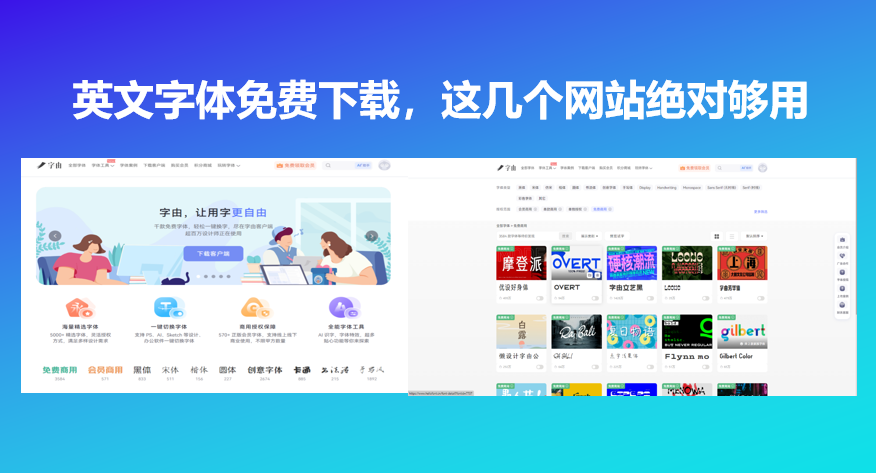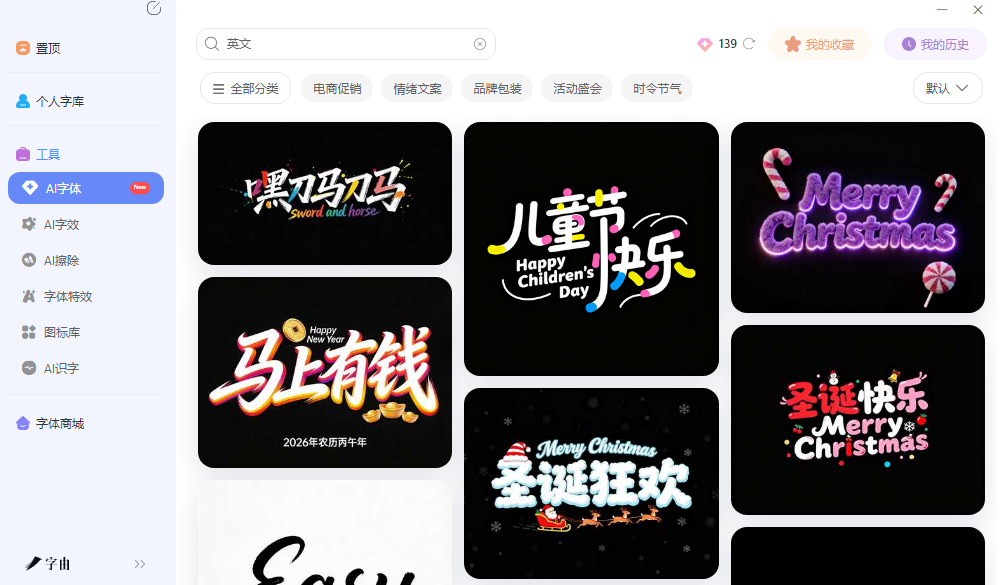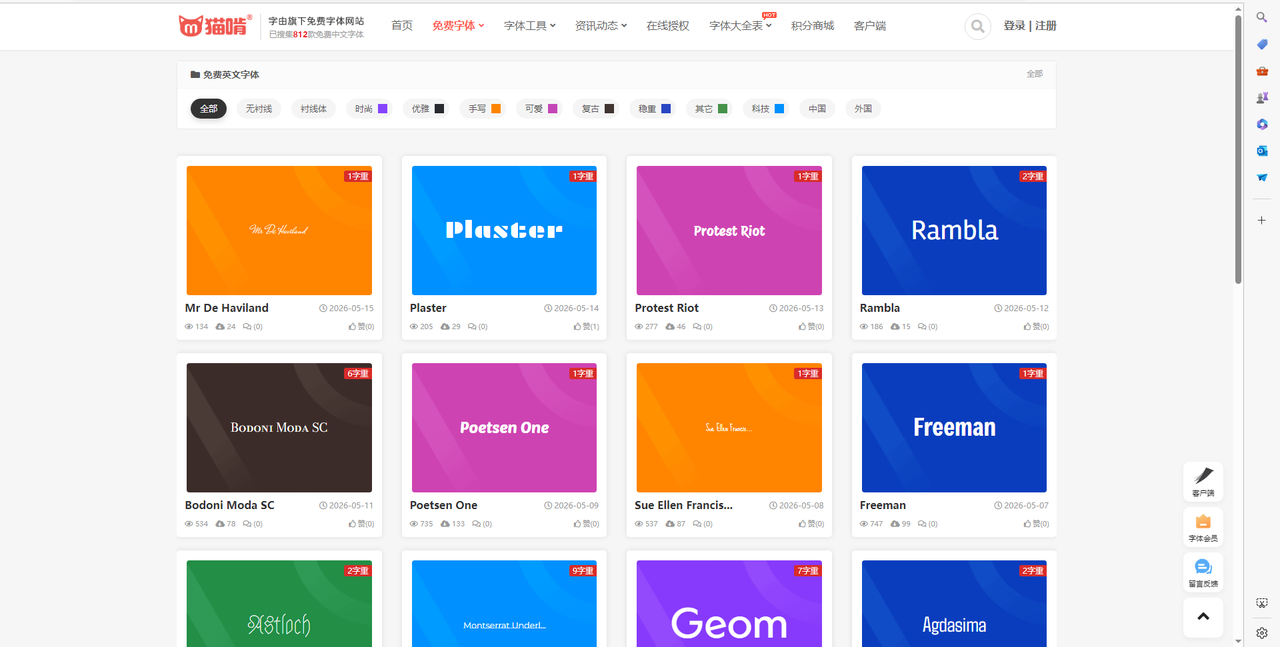
英文字体免费下载,这几个网站绝对够用
打开PS准备做一张英文海报,字体下拉菜单翻来翻去就那么几款:Arial、Times New Roman、Helvetica。不是不好用,是每个项目都用,做出来的东西跟别人的放在一起,分不清是谁的。去网上搜“免费英文字体”,结果不是收费就是版权不明,要么下载流程繁琐得让人想放弃。其实真正好用的免费英文字体下载站就那几个,有的不用下载直接激活,有的精选开源字库,有的分类细致到能按风格一键筛选。今天说5个我亲测好用的渠道,从字由的云端激活到垂直开源站,每个都能让你找到既免费又能放心用的英文字体。
字由和传统字体下载站最大的区别是:你不需要下载任何字体文件。打开字由客户端,里面收录了上万款字体,其中免费商用英文字体占了相当比重。字由的英文字体按风格分得很细。无衬线体适合现代简洁的设计,衬线体适合经典优雅的排版,手写体适合邀请函和个性标题,等宽体适合代码和科技感设计。每款字体都可以实时预览——输入你自己的文案“Hello World”,页面立刻显示效果,不用激活就能判断合不合适。
找到喜欢的英文字体后,点击“激活”按钮。字体立刻出现在你的PS、AI、Word字体列表里,不用下载安装包,不用解压,不用重启软件。换电脑时登录同一个字由账号,之前激活的字体一键同步,不用重新下载。对于经常在多台设备之间切换的设计师来说,字由是最省事的方案。
字由的AI字体功能也可以生成英文艺术字。在AI模板里搜索“英文字体”“霓虹”“金属”,选一个模板输入英文,生成高清PNG图片,背景透明,直接放在海报里。如果你只需要一张特效英文标题图,AI字体是更快的路子。
2、猫啃网
第二个网站是猫啃网。它自称“字由旗下免费字体网站”,已搜集812款免费中文字体,同时也收录了大量高品质免费英文字体。从第一张截图可以看到,它专门设有“免费英文字体”板块,分类包括无衬线、时尚、优雅、可爱、复古、稳重、科技、中国、外国等。用户可以根据项目调性快速筛选。主页展示了多款免费英文字体:Mr De Haviland(手写花体)、Plaster(粗犷展示体)、Protest Riot(街头风格)、Rambla(优雅无衬线)、Bodoni Moda SC(经典衬线)、Poetsen One(圆润标题体)、Sue Ellen Francisco(手写草书)、Freeman(现代粗体)、Agdasima等。
猫啃网的字体会员专区还提供了多字重字体,如6字重、9字重、7字重的完整家族,适合需要精细排版的专业项目。下载方式:点击字体进入详情页,找到下载链接即可获取TTF或OTF文件。这个站的特点是更新快、分类细,而且所有字体都经过授权确认,免费商用有保障。如果你习惯下载字体文件安装到电脑里使用,猫啃网是首选。
3、Feroniapi
第三个网站是一个单体字体下载页面。它展示了“Mating curry wurst”字样和“Feroniapi”字体,由Peter Wiegel设计,并有Julienne Richard的贡献。页面提供了“Download”按钮。这类单体字体站通常由设计师个人维护,字体质量高,且大多免费商用。Feroniapi是一款带有手写感或装饰感的英文字体,适合标题或短句。单体字体站的优势是直接、无广告、下载快速。缺点是字体数量少,需要用户主动搜索。如果你已经知道想要的具体字体名称,或者喜欢挖掘小众设计师的作品,可以关注这类站点。通常从设计师的个人网站或Behance页面找到下载链接。下载后直接安装到系统字体文件夹即可使用,注意查看字体包内的授权说明。
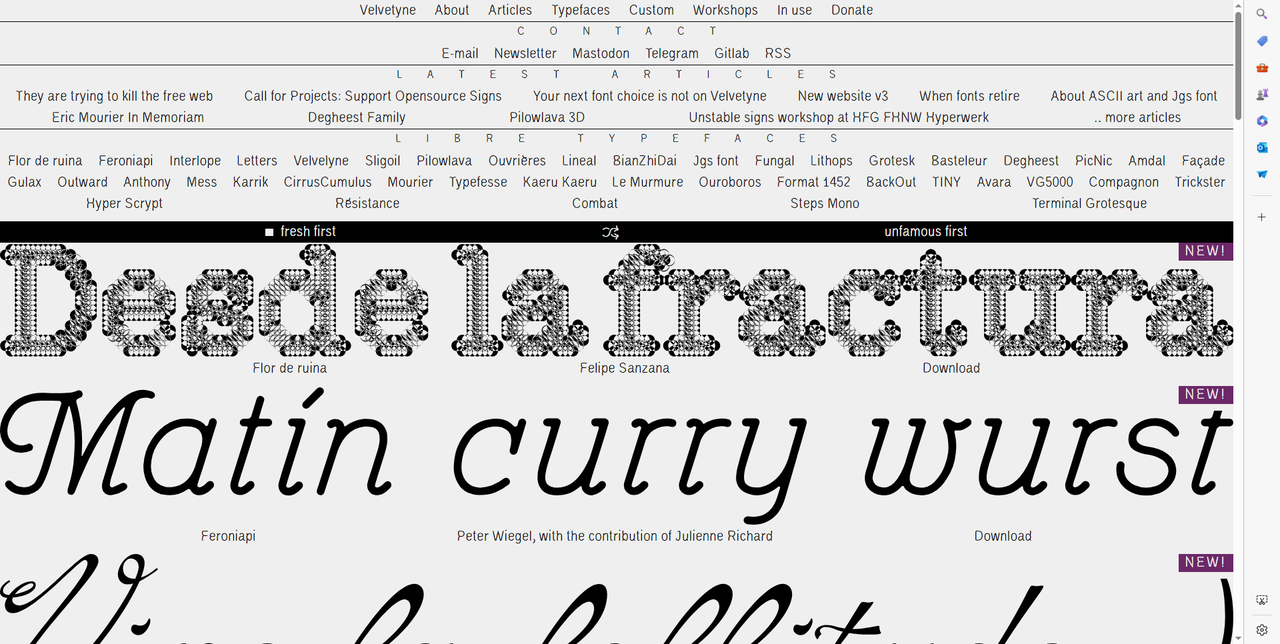
4、Open Foundry
第四个网站是Open Foundry。这是一个专注于开源字体的平台,界面极简。截图显示它展示了“M+ M Type-1”等开源字体,并提供“Subscribe”订阅功能。Open Foundry的字体大多是SIL OFL协议或CC0协议,可免费用于个人和商业项目,并且允许修改和再分发。Open Foundry的风格偏向现代、极简、实验性,收录的字体不像传统字体站那么多,但每款都是精品。如果你需要一款有设计感、不落俗套的开源英文字体,这里值得一逛。下载方式:点击字体卡片进入详情页,找到下载链接或GitHub仓库。这个站适合追求独特、不撞字体的设计师,以及需要嵌入网页的开源项目。
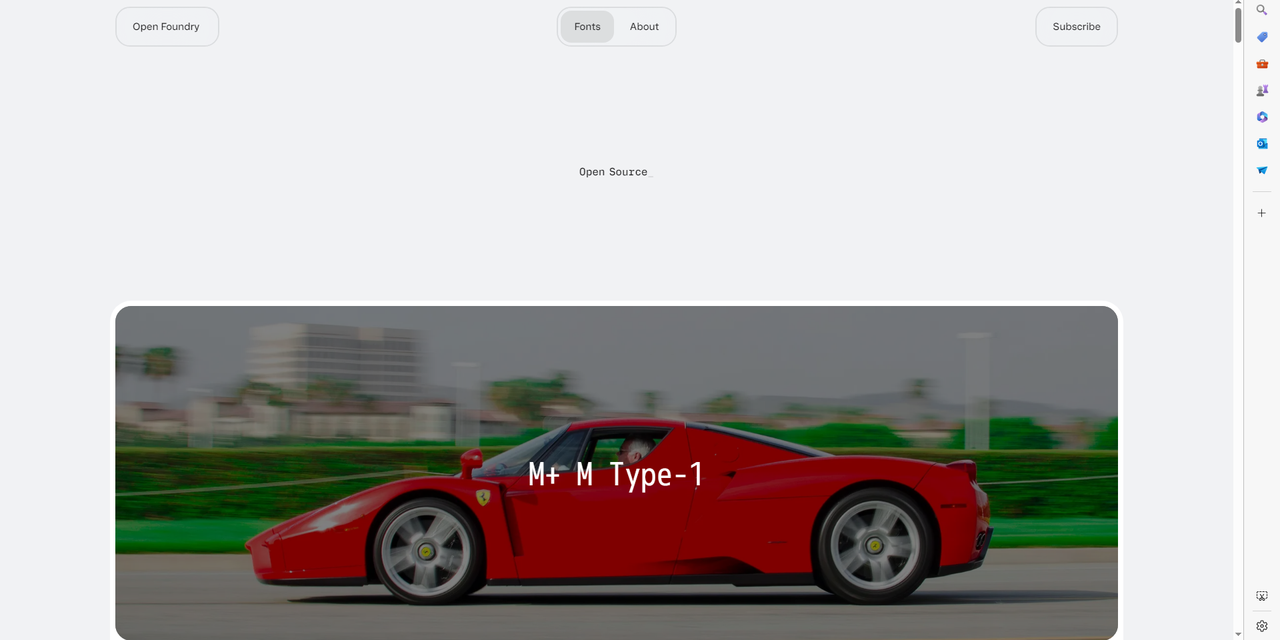
5、popular free fonts
第五个网站是一个热门免费字体集合站。它推荐了多款特色免费字体,包括:
- Nintendo(任天堂风格,怀旧游戏感)
- Pretendo(个人使用,复古像素风)
- SteelTongs(电影配乐主题,无衬线)
- Ravenscroft Regular(尖刺哥特感)
每款字体都标注了标签,如“nostalgic”“playful”“video-game-inspired”“heavy”“display”“retro”等,方便按风格查找。下载按钮直接提供TTF文件。这个站的特色是字体风格非常鲜明,很多是致敬流行文化的设计,适合做特定主题的海报、游戏UI、音乐封面。授权方式各不相同,有的仅限个人使用,下载前需查看说明。如果你不满足于普通字体,想要一些有个性、有话题性的英文字体,这个站是宝藏。
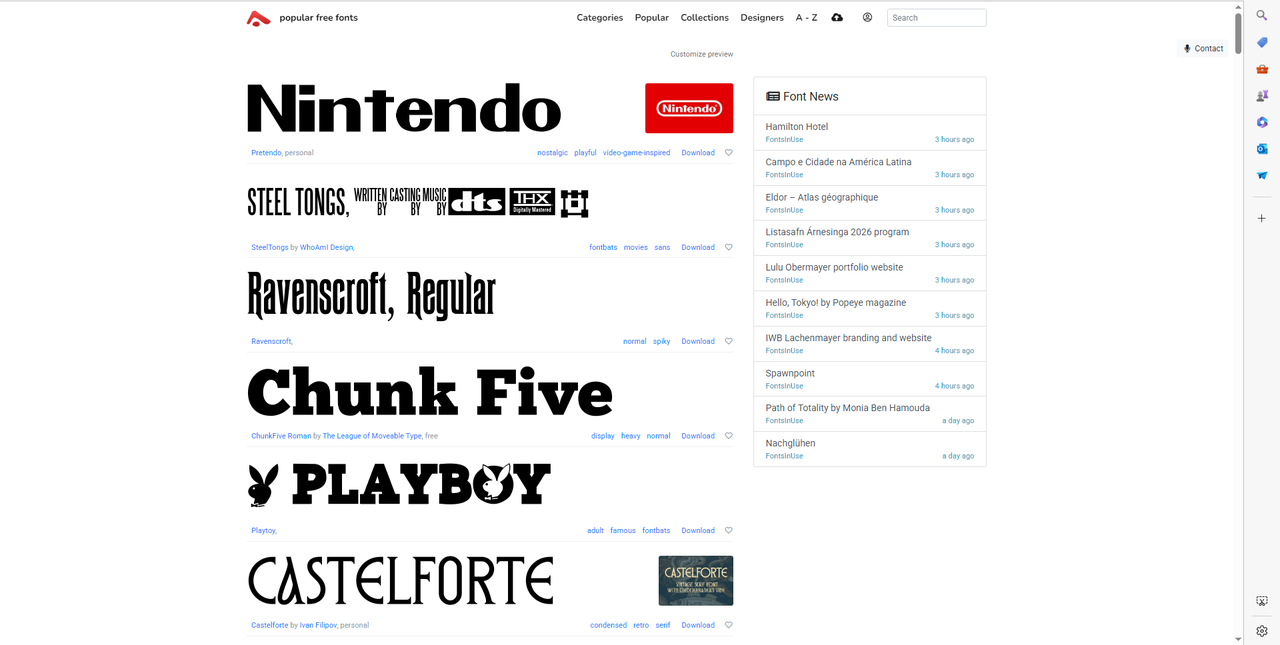
这几个英文字体网站都是实打实的好用,随便拿出来一个其字体量都足够大,不怕你找不到自己喜欢的字体,而且字由最适合不想折腾安装、追求效率的设计师,不用下载点一下就能用,跨设备同步也方便;猫啃网分类清晰、更新快,英文字体按风格筛起来很顺手;Feroniapi这类单体字体站适合挖掘小众设计师作品,下载直接没广告;Open Foundry是开源爱好者必逛,每款都是精品且协议宽松;popular free fonts集合站专供特色款,游戏、复古、哥特风格应有尽有。如果你也想试试新字体那就快打开网站试试吧!